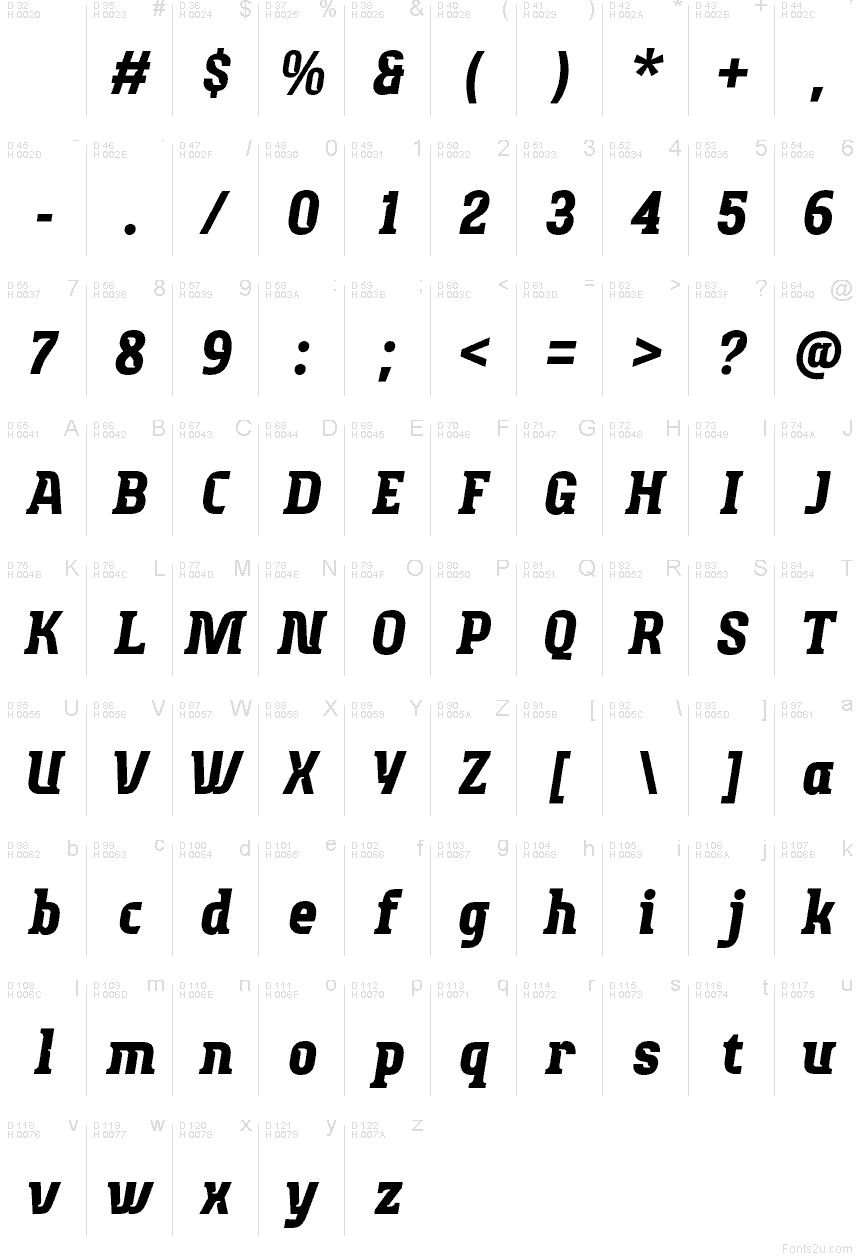
Runzoe Italic, une police d'affichage italique moderne et gratuite créée par Afakari Studio, apporte une touche dramatique audacieuse et rétro à ses lettres inclinées. Ses empattements épais et doucement arrondis ainsi que ses courbes profondes créent un rythme fluide et théâtral, tandis que son inclinaison prononcée vers l'avant insuffle du mouvement à l'ensemble.
Cette police gratuite est idéale pour les éditos mode, les pochettes d'album, les titres d'affiches, l'identité visuelle de restaurants et les cartons de titres où une phrase courte doit porter la composition. Utilisez-la pour des titres de couverture, des noms de campagne ou de grands logos typographiques lorsque ses empattements imposants et son inclinaison énergique doivent dominer la mise en page.
Designed by Afakari Studio.